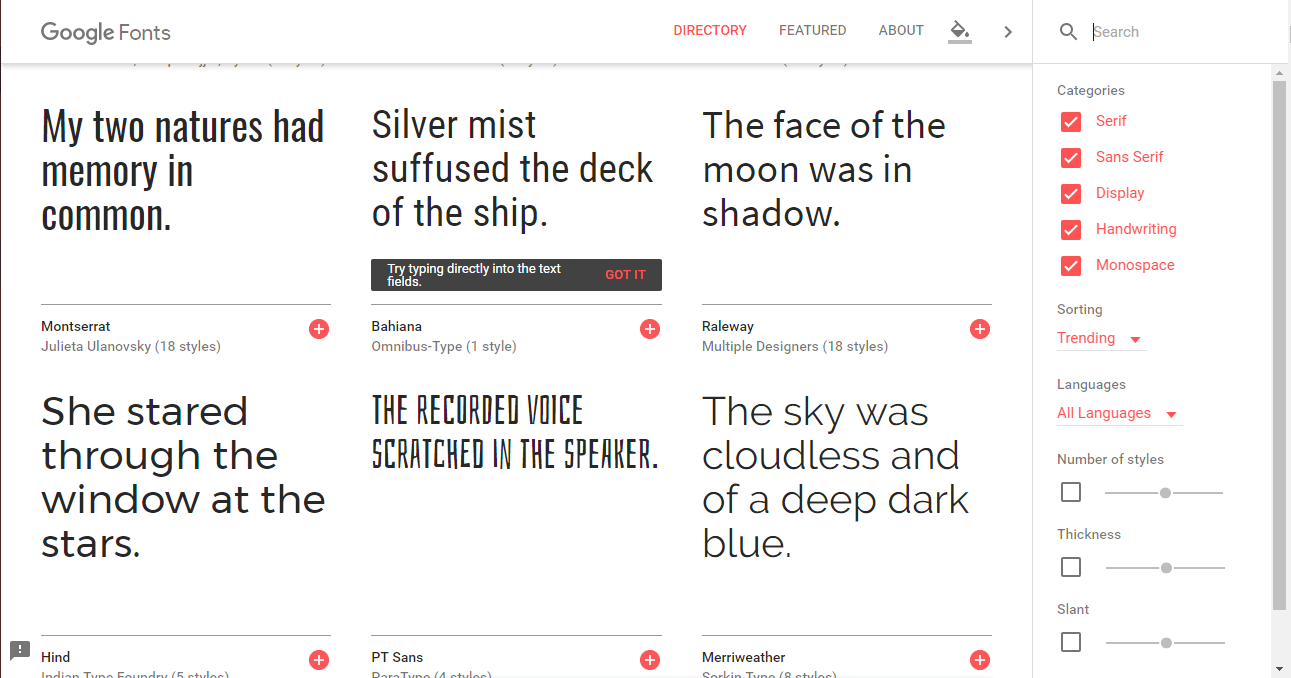
Dai al tuo sito un restyling dei caratteri
Pubblicato: 2017-02-20Quando siamo entrati nel nuovo anno, abbiamo provato ogni cosa possibile per cambiare la nostra presenza online in un modo migliore in modo che potesse sembrare buono per un potenziale cliente di nuova visita. Senza dubbio, l'aspetto dei nostri siti Web influisce sulle decisioni di acquisto dei nostri potenziali clienti. Laddove abbiamo provato e testato così tante cose, perché non dare un restyling dei caratteri al nostro sito Web in modo che rilasci l'impatto tanto necessario sul visitatore del tuo sito.
Parliamo di alcuni possibili rinnovamenti che possiamo fare al nostro sito, il mio consiglio è di iniziare con la tipografia.
Passaggio 1. Come appare la tipografia attuale del tuo sito Web WordPress?
Prima ancora di iniziare qualsiasi modifica al tuo sito, valuta ciò che hai attualmente e, soprattutto, come stanno andando le cose nel tuo settore di nicchia. Ti suggerirò di analizzare alcuni concorrenti di prim'ordine della tua nicchia. Guarda le prestazioni del loro sito a seconda di come hanno organizzato i caratteri e la tipografia.
Per valutare la tipografia di un sito web, poniti le seguenti domande:
1. Da dove provengono i caratteri attuali?
Sei a conoscenza di come sono nate le attuali selezioni dei caratteri del tuo sito? Se il tuo sito utilizza i caratteri predefiniti del tuo tema WordPress o sono stati scelti per capriccio, di solito è un buon segno che devono essere cambiati. Anche se probabilmente sembrano abbastanza belli , non sono stati selezionati a mano per adattarsi allo stile unico del tuo marchio. La coerenza nel design è fondamentale, dalle immagini che utilizzi fino alla tipografia.
2. La tua famiglia di caratteri è completa?
Va bene, quindi ora, dopo molte ricerche e impegno, abbiamo finalmente trovato i caratteri più adatti, quelli che si adattano bene al nostro sito e danno un aspetto nuovo e attraente al nostro sito web. Ma è completo? o solo una versione più breve di ciò che verrà lanciato in seguito. In breve, la domanda che dovrebbe sorgere nella tua mente è se i caratteri che hai selezionato sono completi o meno?
Se non sei sicuro di avere o meno un carattere tipografico completo che includa tutte le lettere, i numeri e i simboli, torna all'origine del carattere. Dovrebbe esserci un campo di anteprima in cui puoi inserire testo personalizzato. Inserisci le seguenti righe di testo per assicurarti che tutti i caratteri essenziali siano presenti:
3. Ci sono problemi di leggibilità?
Utenti Mac, vi suggerisco di scaricare Font Book. Dopo aver scovato il carattere di tuo interesse, installalo nel Libro dei caratteri per verificare la presenza di problemi di leggibilità. Puoi usarlo per:
- Verifica la presenza di un set completo (come con il test n. 2 sopra).
- Visualizza l'anteprima digitale del carattere per avere un'idea di come apparirà sul tuo sito web.
- Stampa l'intero set di caratteri in diverse dimensioni e stili per determinare quali sono i più facili da leggere.
Questo è anche un ottimo strumento per archiviare i tuoi caratteri e tenerli organizzati per la prossima volta che vuoi dare un nuovo look alla tua tipografia.
4. Come appare sul cellulare?
Esistono alcuni strumenti gratuiti online come Responsinator che semplificano notevolmente la verifica della compatibilità reattiva. Questi stessi controlli reattivi possono essere utilizzati anche per rivedere la tipografia del tuo sito per l'ottimizzazione dei dispositivi mobili.
La raccomandazione standard per il dimensionamento dei caratteri multipiattaforma è di 16 punti o più. Potrebbe non essere il caso se scegli un carattere altamente stilizzato o con una crenatura stretta, quindi assicurati di verificarlo su uno di questi strumenti prima di impegnarti.
Puoi anche utilizzare questa guida al dimensionamento dei caratteri più diffusi per darti un'idea di dove iniziare con il restyling dei caratteri.
5. Il colore del tuo carattere è adatto alla lettura?
Rinnovare il tuo sito con il corretto set di caratteri e rendere la dimensione ideale per il lettore non è l'unica cosa da fare.
No, si tratta anche di trovare il colore giusto. Se non hai ancora sperimentato questa tavolozza di design dei materiali, prenditi un momento per farlo ora. Vedrai che, indipendentemente dai colori di branding selezionati, il colore del carattere primario e secondario sono sempre nero o una sfumatura di grigio.
6. Che ne dici dell'accessibilità?
Gli sviluppatori web sanno tutto su come rendere accessibili i siti web. Tuttavia, se stai davvero cercando di dare alla tua tipografia una compatibilità universale in questa prossima iterazione, presta maggiore attenzione ai fattori che possono influenzare coloro che sono ipovedenti o daltonici.
Inizia eseguendo il tuo sito Web tramite Color Oracle. Questo strumento simulerà l'aspetto del tuo sito Web a coloro che sono daltonici.
Spero che questi pochi suggerimenti e trucchi per il restyling dei caratteri ti aiutino a rinnovare il tuo sito per aumentare più visitatori.